Microsoft Officeアプリは、新しいデフォルトのフォントとテーマを取得します。新しいフォントであるAptosは、Word、Excel、PowerPoint、およびOutlookのデフォルトのフォントとしてCalibriを置き換えます。
Aptosフォントとともに、新しいカラーパレット、スタイル、ラインウェイトで更新されるマイクロソフトオフィスアプリ
マイクロソフトはです計画来月、オフィスアプリの新しいデフォルトフォントとテーマをロールアウトします。同社は、新しいAPTOSフォント、新しいカラーパレット、スタイル、更新されたデフォルトのラインウェイトでデフォルトのオフィステーマを復活させていると言います。
新しいデフォルトのテーマは、エンドポイント全体でWord、Excel、PowerPoint、およびOutlookに登場します。新しいテーマには、新しいデフォルトフォント、適切なカラーパレット、更新されたデフォルトのラインウェイトが含まれます。
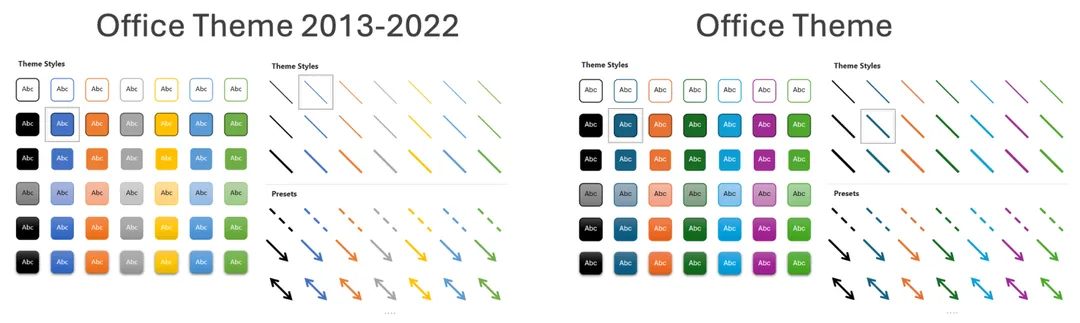
新しいAptosフォント、新しいカラーパレット、スタイル、更新されたデフォルトのラインウェイトを備えた新しいデフォルトのMicrosoft Officeテーマの詳細
aptosフォント
Aptosは、20世紀半ばのスイスのタイポグラフィに触発されたSans-Serifの書体です。現在のデフォルトフォントであるCalibriよりも読みやすく多用途になるように設計されています。 Aptosには、LightからHeavyまでの幅広い重量があり、さまざまなドキュメントタイプに適しています。
カラーパレット
オフィス用の新しいカラーパレットは、古いものよりもモダンで活気があります。黄色は除去され、濃い緑に置き換えられました。この変更は、Microsoft Officeアプリをより視覚的に魅力的で読みやすくすることを目的としています。新しいカラーパレットには、より広い範囲のシェードも含まれています。これにより、ユーザーはドキュメントを作成するときにより多くのオプションを提供します。
スタイル
Microsoft Officeアプリのデフォルトスタイルは、より近代的で一貫性があるように更新されています。新しいスタイルは、タイポグラフィの階層の原則に基づいています。つまり、異なるフォントサイズとウェイトを使用して、ドキュメントに明確な視覚階層を作成することを意味します。これにより、読者がドキュメントをスキャンして理解しやすくなります。
ラインウェイト
Microsoft Officeのデフォルトのラインウェイトは、オフィスアプリをよりモダンに見せるために増加しています。新しいラインのウェイトはより一貫しているため、ドキュメントがより洗練されているようになります。